日向数夫氏編集「新装版 江戸文字 (グラフィック社の文字シリーズ) 」
日向数夫氏編集による勘亭流や寄席文字といった江戸時代につくられた書体・江戸文字を紹介した「新装版 江戸文字 (グラフィック社の文字シリーズ)」がグラフィック社から新装版として2016年8月5日に発売されている。
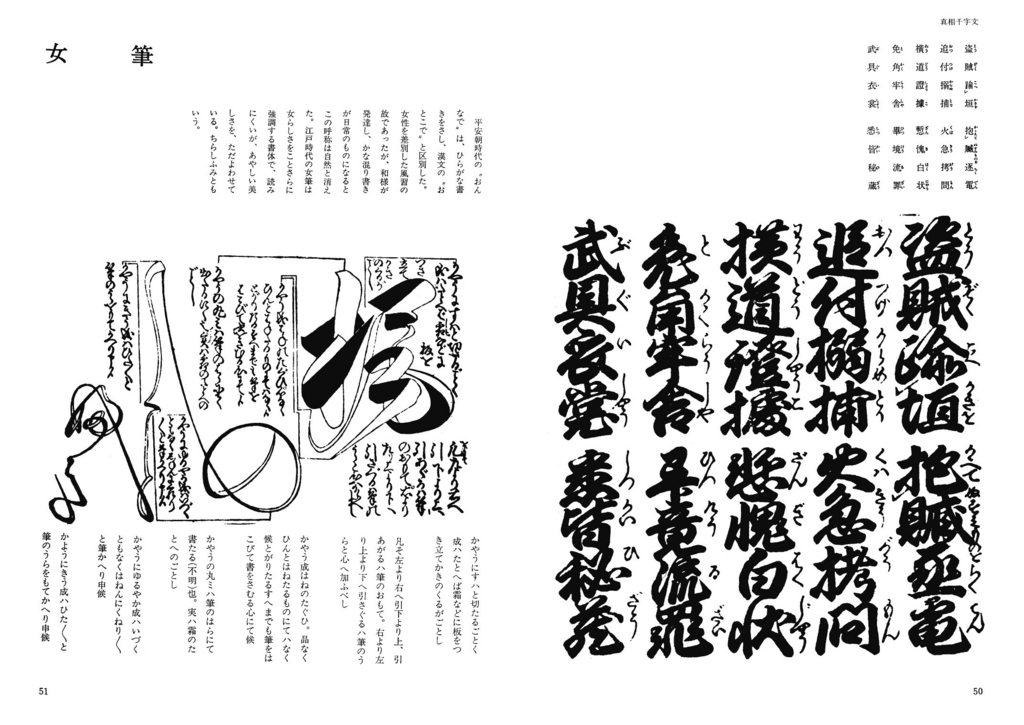
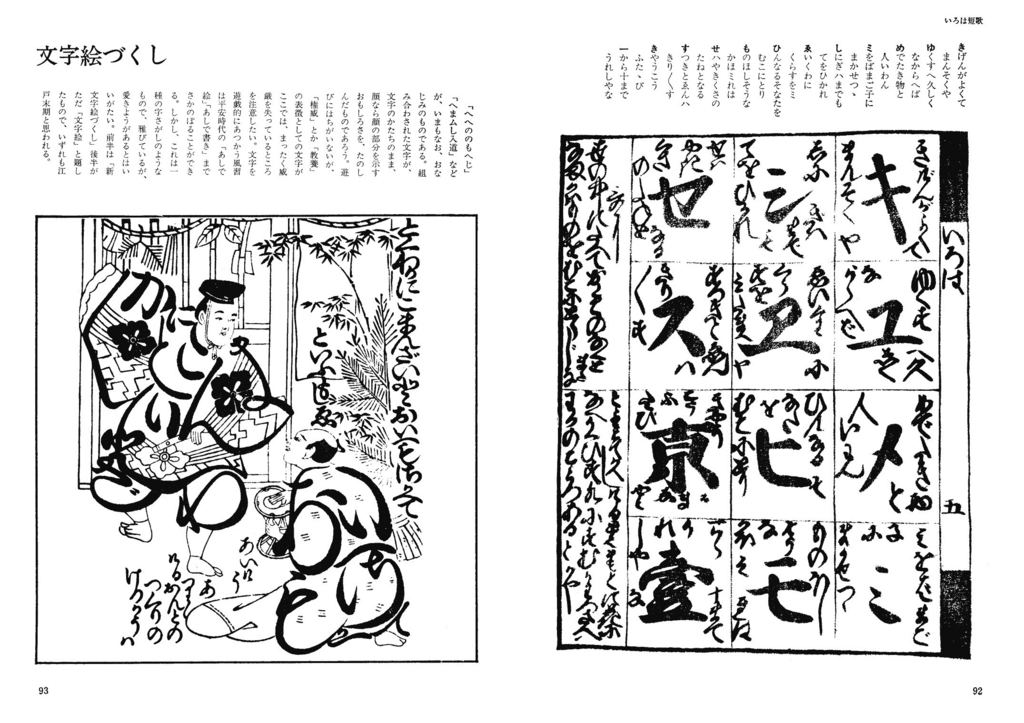
江戸文字が粋なものであるか、意気なものであるかは本書が語る
勘亭流、寄席文字、浄瑠璃文字、籠字、角字、歌舞伎文字、謡曲文字、相撲文字、まとい文字、ひげ文字、また草双紙、千社札、百人一首、将軍印などに使われた文字まで網羅した、「江戸文字」についての決定書、待望の復刊!